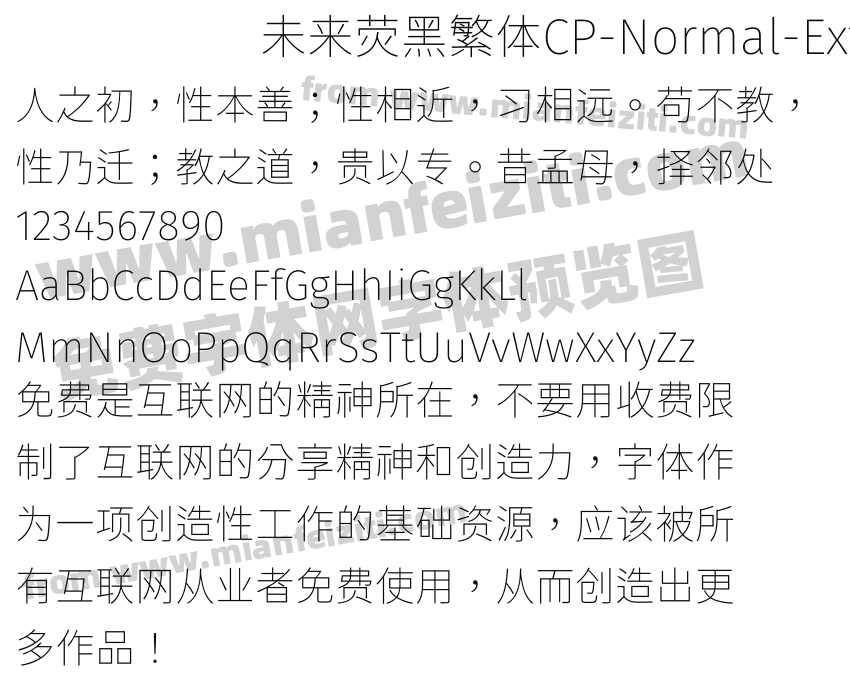
未来荧黑繁体CP-Normal-ExtraLight
字体名称: 未来荧黑繁体CP-Normal-ExtraLight
Postscript名称: GlowSansTC-Normal-ExtraLight
字体版本: Version 0.9
字体字重: ExtraLight
未来荧黑繁体CP-Normal-ExtraLight预览图1
未来荧黑繁体CP-Normal-ExtraLight预览图2
未来荧黑繁体CP-Normal-ExtraLight字体映射图
本款“未来荧黑繁体CP-Normal-ExtraLight”是一款书写很新颖的字体,字体大方,适合各种设计作品使用!欢迎下载!